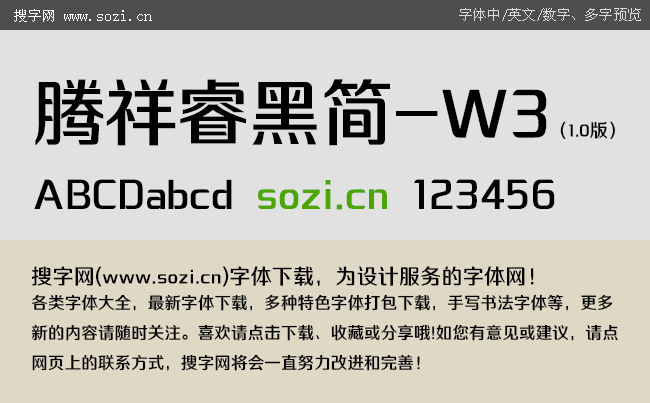
騰祥睿黑簡(jiǎn)-W3
搜字網(wǎng)提供一款非常藝術(shù)的黑體字騰祥睿黑簡(jiǎn)-W3下載,騰祥睿黑簡(jiǎn)是一款應(yīng)用于設(shè)計(jì)方面的藝術(shù)黑體,字字精美、結(jié)構(gòu)端正、重心平穩(wěn)、美觀實(shí)用,其中W3粗細(xì)適中,適用于包裝印刷、廣告設(shè)計(jì)、平面設(shè)計(jì)、書(shū)籍報(bào)紙等領(lǐng)域。